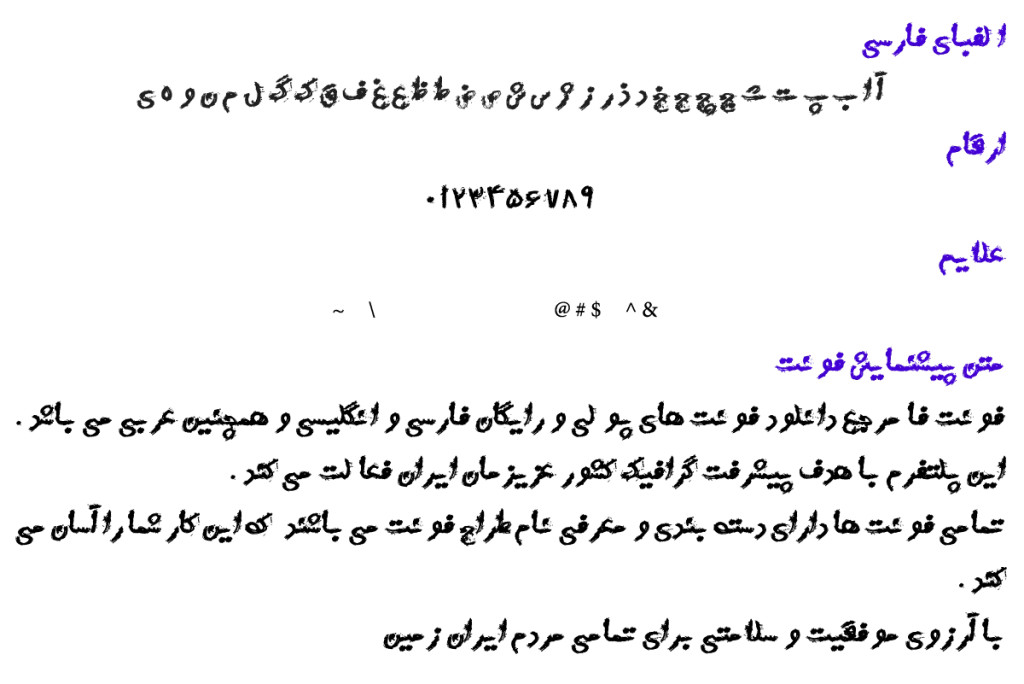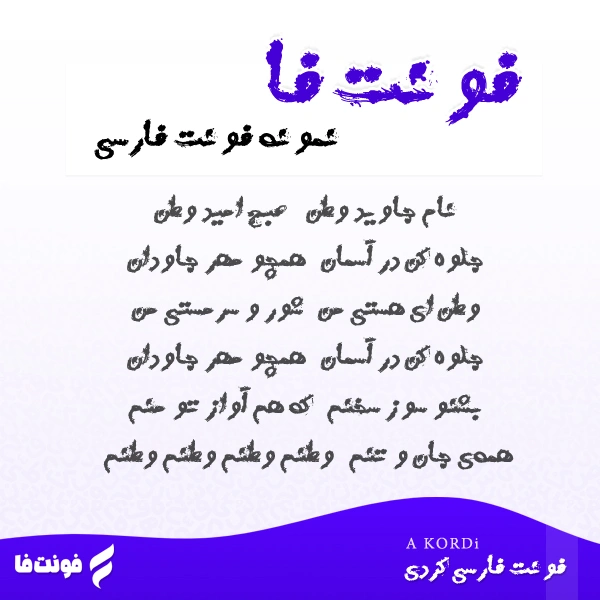
فونت فارسی کردی – A KORDi
طراح فونت: امید کردی نوع فونت: فونت گرافیکی
توضیحات و معرفی فونت کردی
فونت فارسی کردی ( A KORDi ) از مجموعه فونت های آزاد می باشد، و نیز نوع فونت گرافیکی می باشد.
فونت خوشگل مربوط توسط امید کردی در سال 1390 طراحی و ساخته شده است.
و نیز فونت A KORDi در یک وزن پر رنگ است.
- A KORDi Bold
در عکس زیر، شعر دل نشین وطن که با این تایپفیس طراحی شده، به نمایش درآمده است.